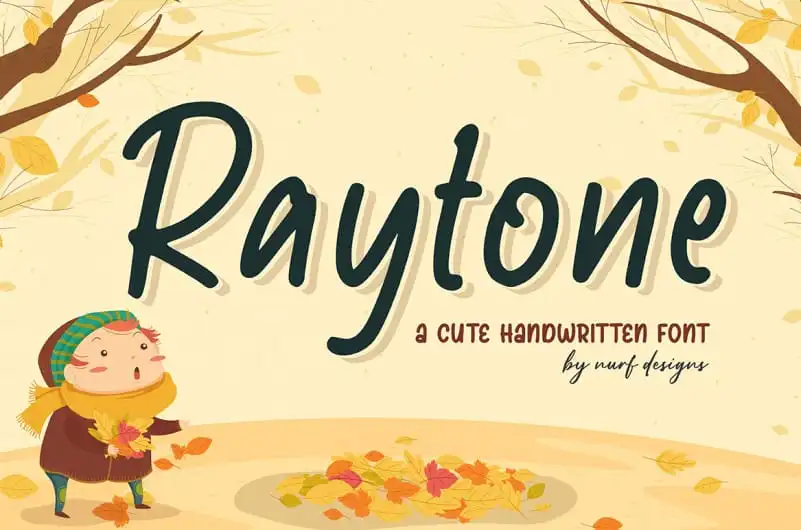
Raytone Script Font – Download Grátis
A Raytone Script Font é uma fonte script divertida para uso de destaque que certamente dará vida aos seus projetos digitais. Seu charme alegre e descontraído faz dela um escolher ótimo para adicionar um toque animado em qualquer projeto infanto-juvenil ou escolar. Essa fonte é ideal para quem busca algo diferente, criativo e divertido que enriqueça sua proposta visual de maneira natural. Com a Raytone Script Font, seus projetos virão à vida com uma personalidade única e encantadora, tornando seu trabalho ainda mais especial.